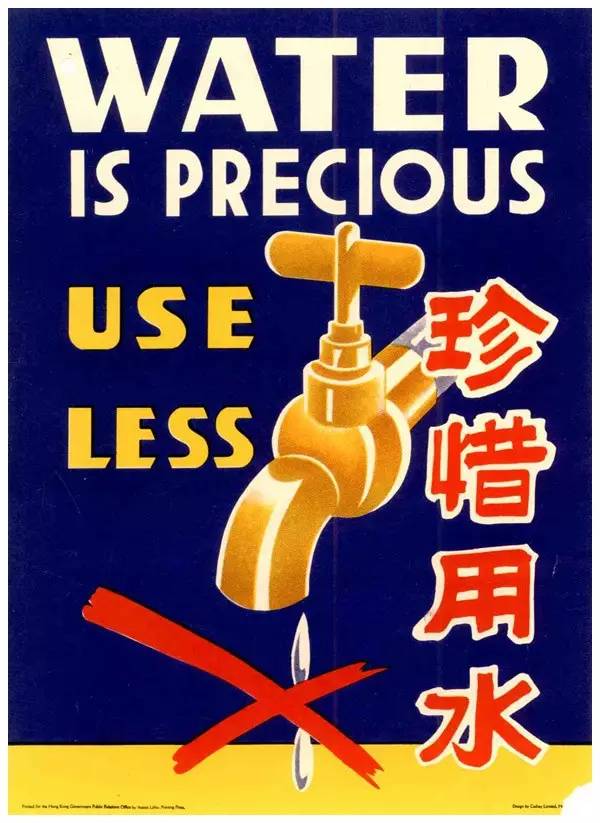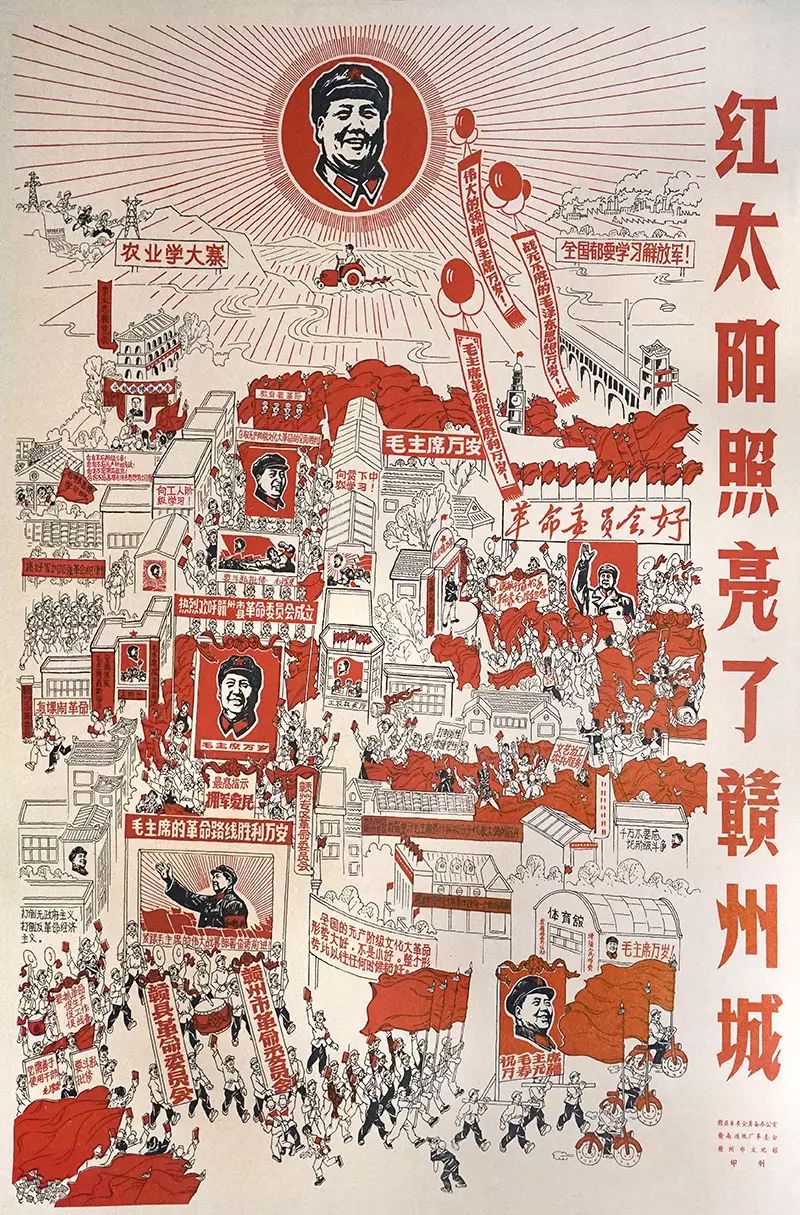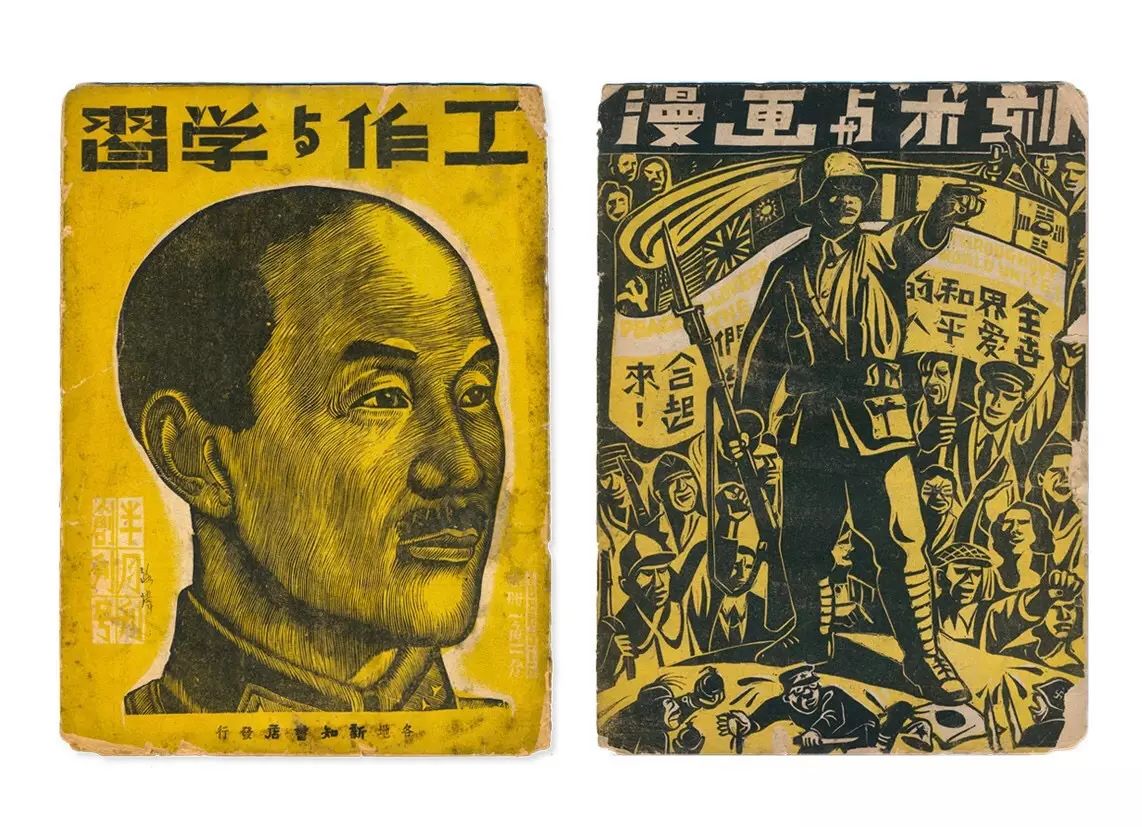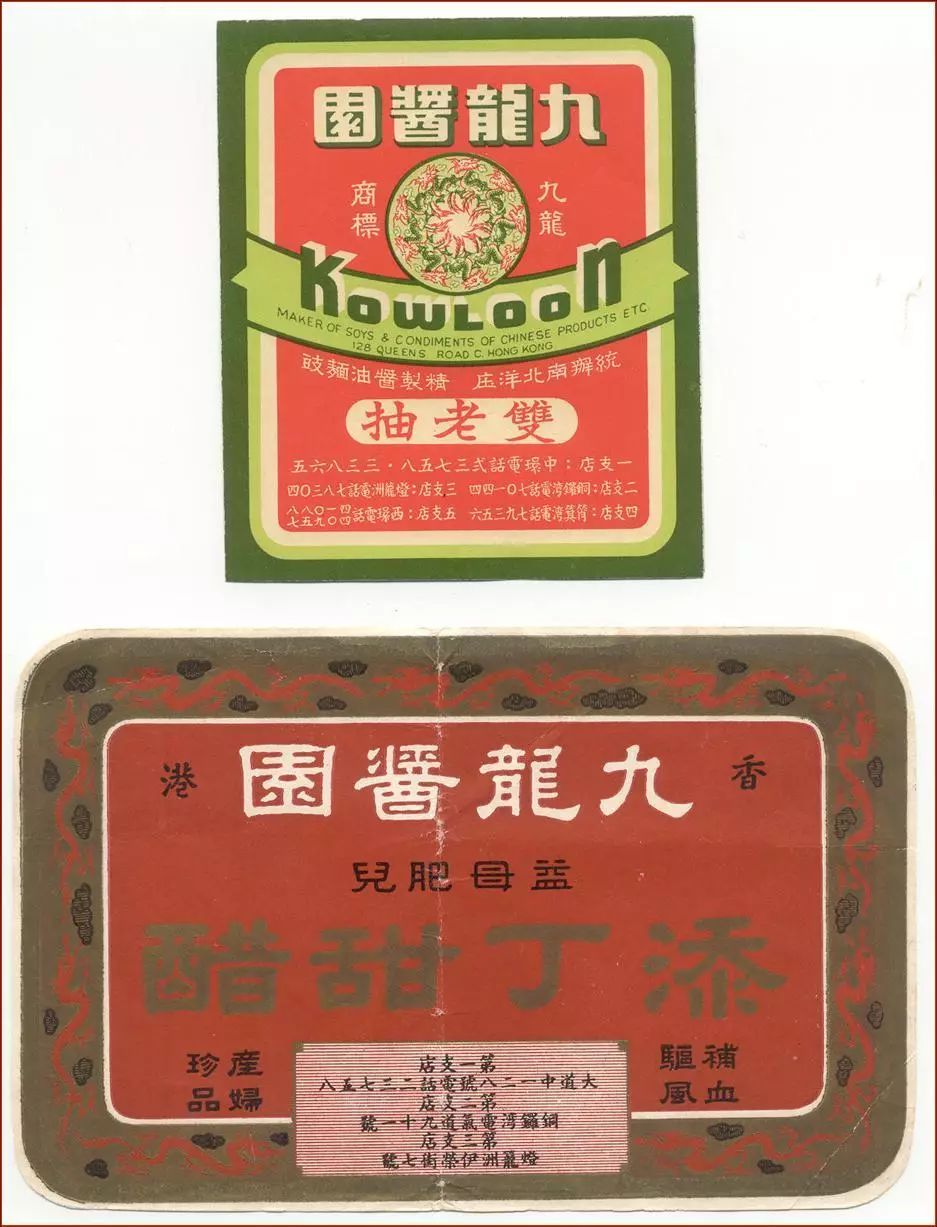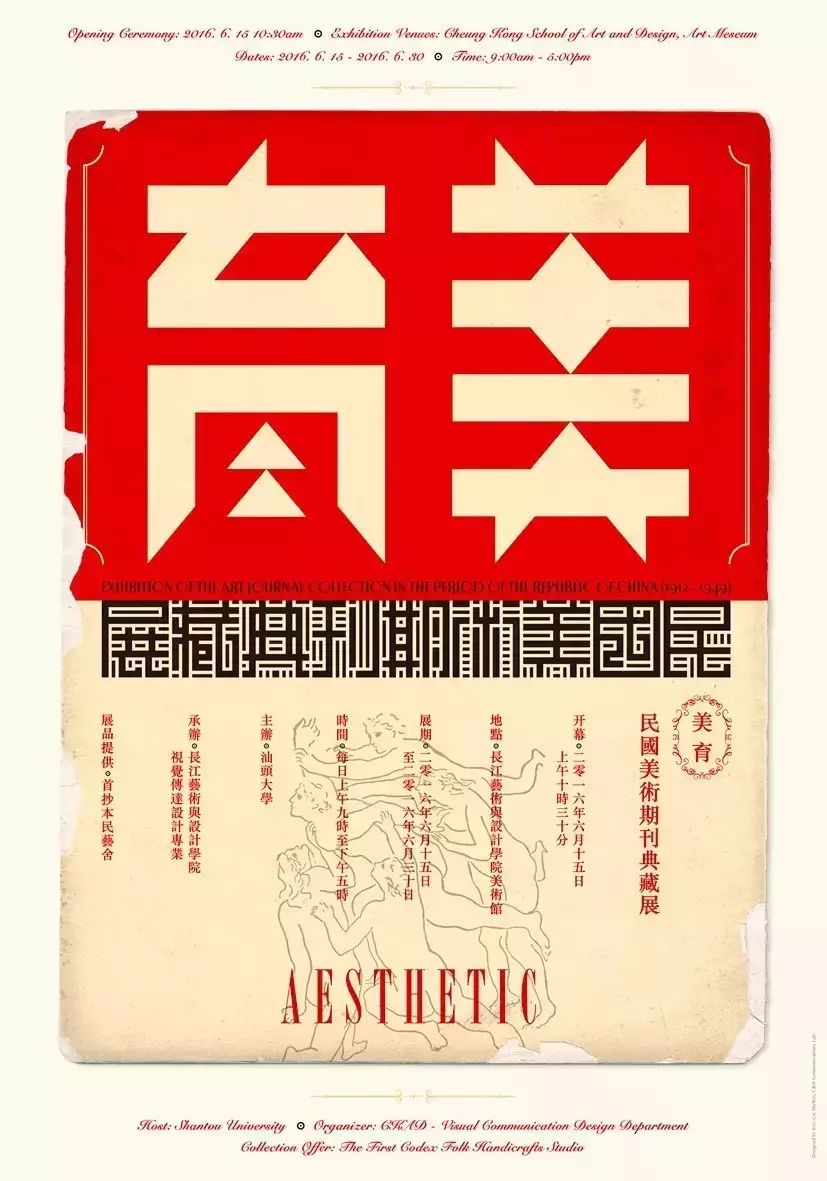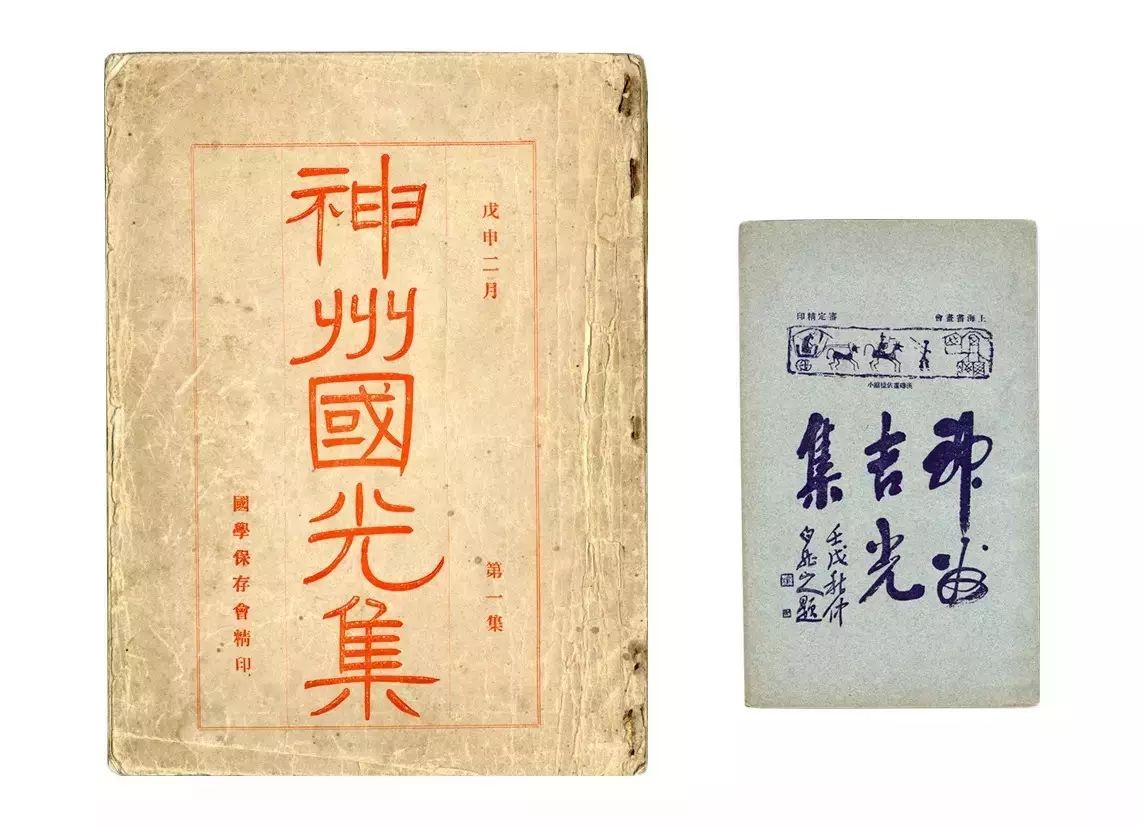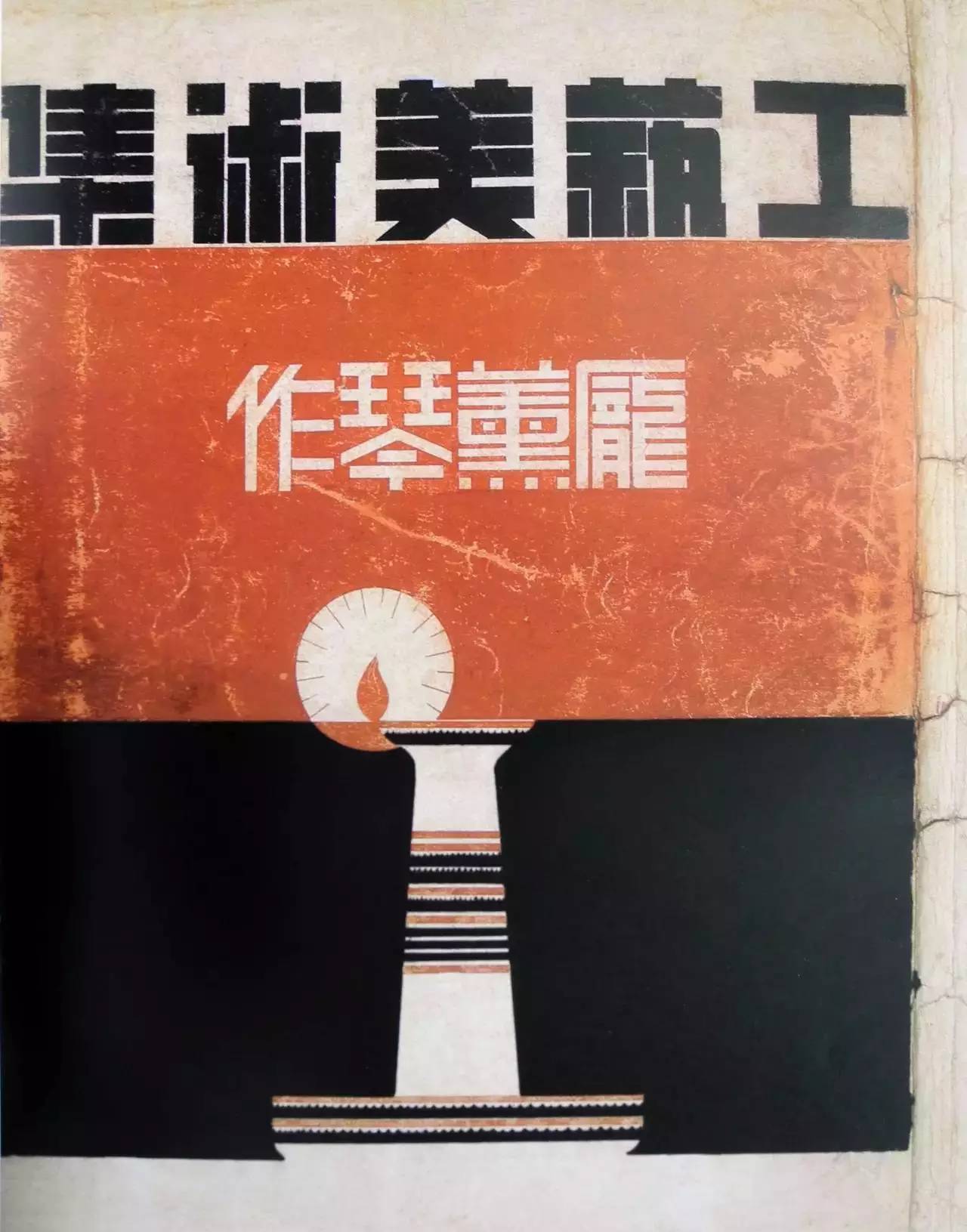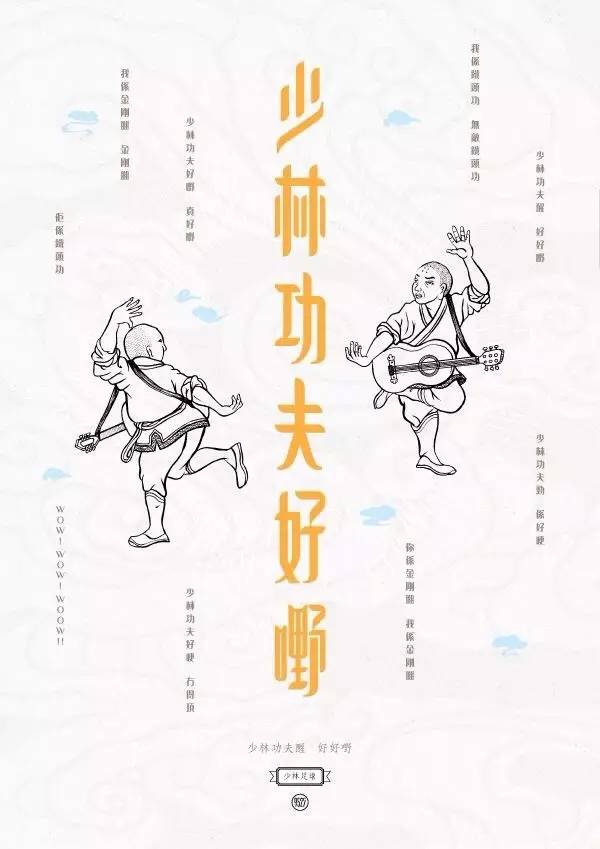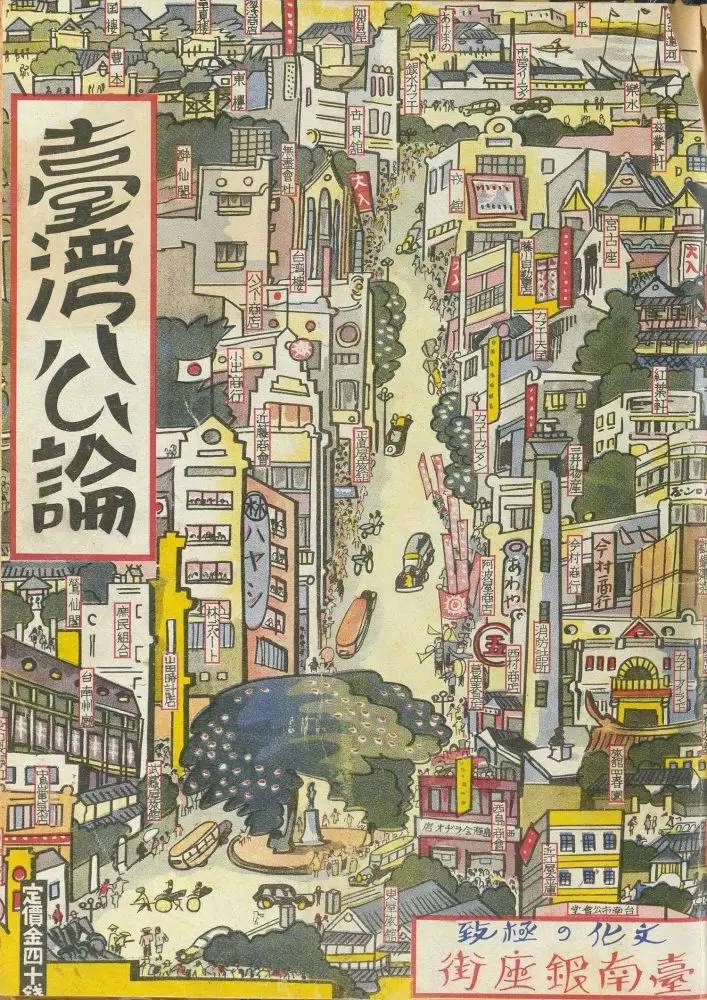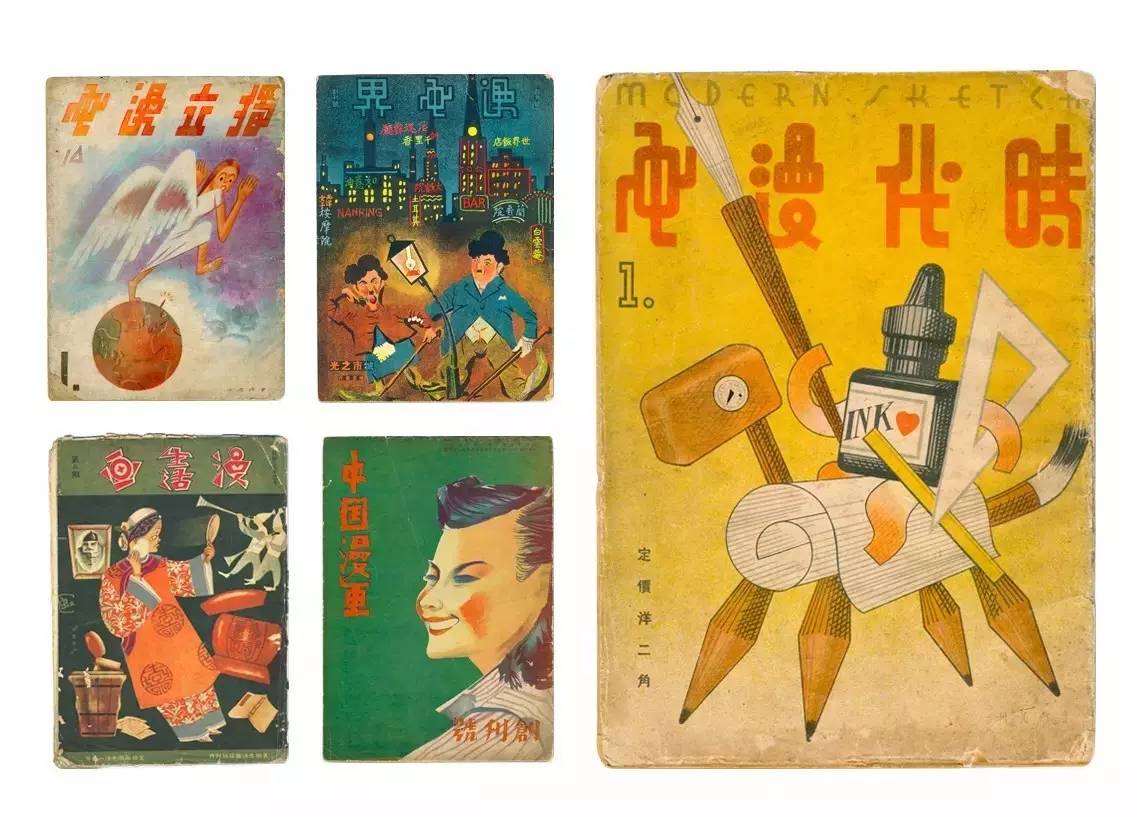
原来老字体设计这么好看!一组老字体设计案例分享
米醋说:汉字是每个设计师必修的课题之一。今天MICU给大家分享一组经过了时间沉淀的老字体,其中的历史感和设计美感总是特殊的,让人回味的!希望能给大家带来一些帮助~
《大闹天宫》在美国上映时的广告
筋斗云
《工艺美术通讯》第1期,1956年
《工作与学习》、《漫画与木刻》
《神州国光集》,神州国光社出版,1908年创刊;《神州吉光集》,上海书画会出版,1922年创刊。
《时代漫画》
封面字体设计
抗战漫画
血项链
珍惜用水
社员俱乐部
报纸字体
鸿馀染织厂
红太阳照亮了赣州城
剃刀边缘
1960年代的香港
暴政火焰山——连环图文
大东南烟草公司出品的白兰地香烟广告
大明火柴
东北抗日小姑娘
敦厚的诈骗犯
服务社會 便利人群 连通城乡繁荣经济
汉方胃肠药:清和錠
红极一时的标志:太阳神
红桃K
九龙酱园
交通部桂黔鐵路工程局(1939)
交通銀行老广告
金瓶梅字体
牛汝森小组.云南人民出版社
抗战必胜连环画
可口可乐1950年的老广告
美育——民国美术期刊典藏展
天津步峰醫院老廣告
香港馬玉山糖果餅干
壹般都市許可
圆明园欧式宫殿残迹
中國銀行天津辦事處老廣告
庞薰琹:工艺美术集 (1941)
仁丹歯磨
日本新青年五月特选集广告
少林功夫好嘢
臺灣公論.第一卷11号